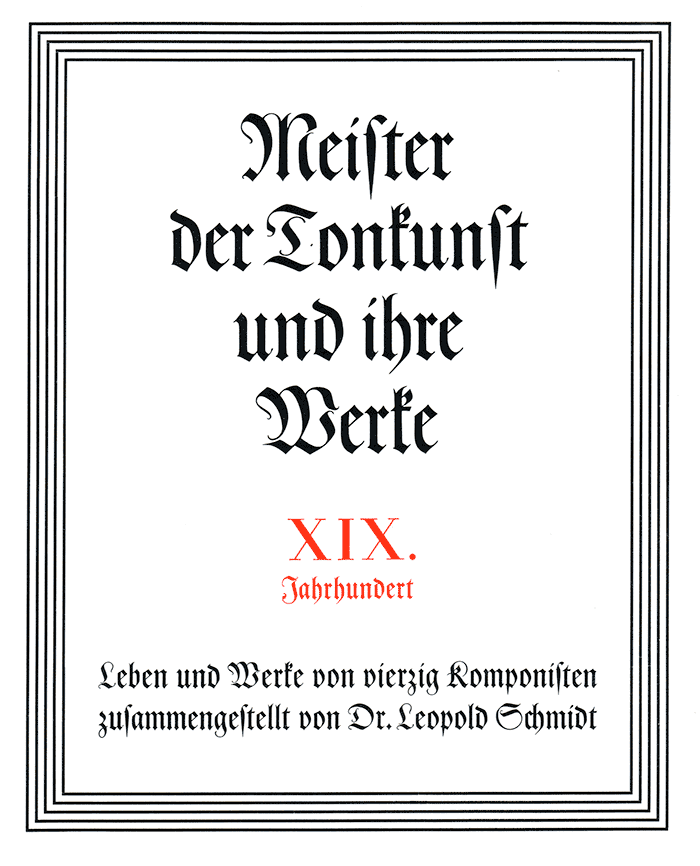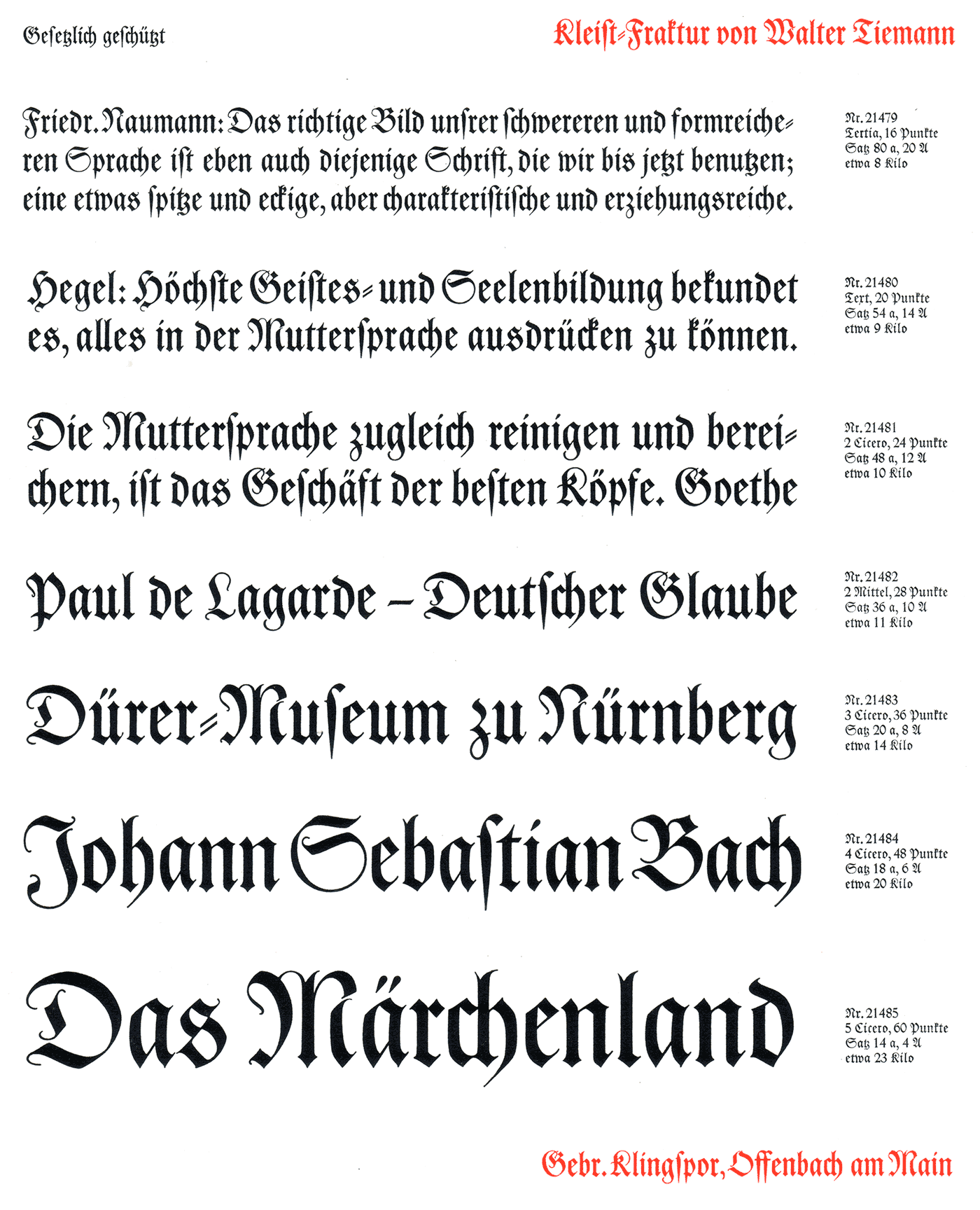
- 1928
- Gebrochene Schrift
Zur Fraktur soll Walter Tiemann (1867–1951) einmal gesagt haben: »Je stärker sich ein Volkscharakter herausbildet, desto eigentümlicher wird er sich im Handschriftlichen und in den Typen bekunden. So ist für mich immer die Fraktur der unmittelbarste und lebendigste Ausdruck für das Faustische im deutschen Menschen gewesen, ohne das doch der Deutsche kein deutscher Mensch sein würde.«
Tiemann widmete mehrere Schriftentwürfe dieser Gattung: die Tiemann-Fraktur/Peter Schlemihl, die Fichte-Fraktur und die Kleist-Fraktur. Letztere war in ihrer Zeit eine bedachte Modernisierung unter Beibehaltung traditioneller Formen und Proportionen. Die barocken Verschnörkelungen sind vor allem bei den Versalien zurückgenommen, aber die Schrift behält ihre kalligrafische Eleganz. Zusätzlich zum Grundschnitt bot Gebr. Klingspor auch ein schwungvolles Initial-Alphabet an.